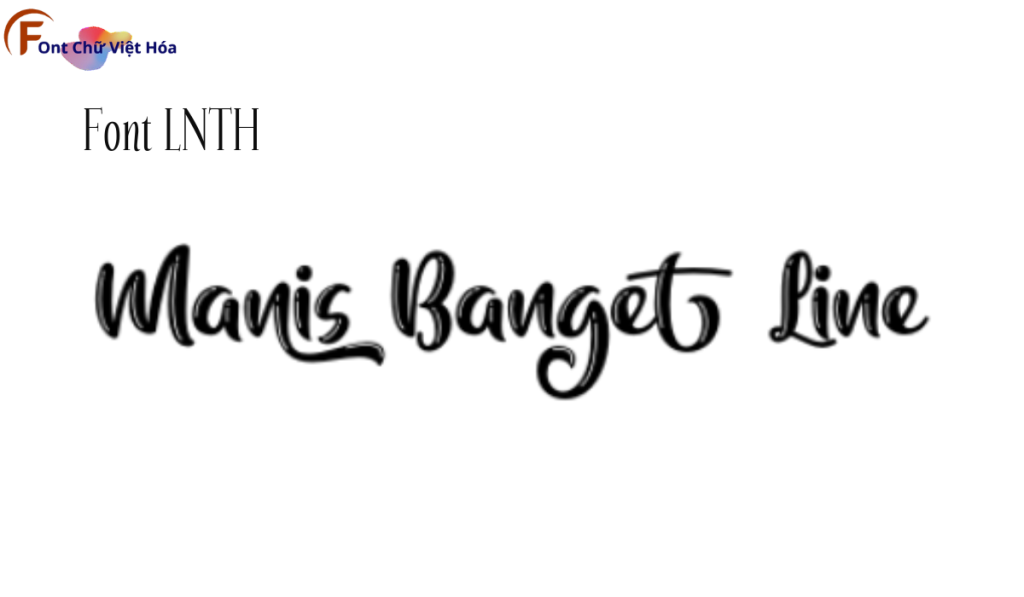
Font LNTH Manis Banget Line Việt Hóa
Font LNTH Manis Banget Line Việt Hóa là một font chữ viết tay mềm mại, thuộc bộ LNTH, với thiết kế uyển chuyển và thân thiện. Phong cách của font này phù hợp với các dự án cần sự tươi mới và dễ gần, như thiệp chúc mừng, thiệp cưới, hoặc banner quảng cáo. Font LNTH Manis Banget Line Việt Hóa mang đến sự mềm mại và dễ nhận diện, ứng dụng trong các lĩnh vực sáng tạo. Đặc điểm hình dạng của font bao gồm các đường nét uyển chuyển và độ dày mỏng hài hòa, giúp tăng tính thẩm mỹ và sự chú ý. Việc Việt hóa font giúp người dùng dễ dàng sử dụng trong các thiết kế tiếng Việt, mang lại sự tiện lợi và linh hoạt.